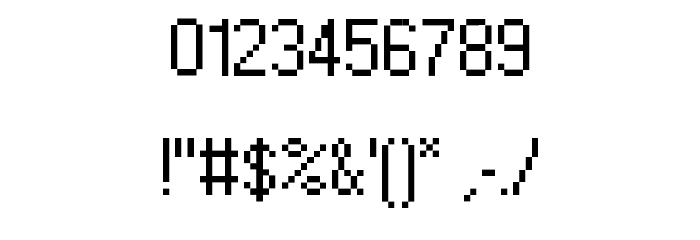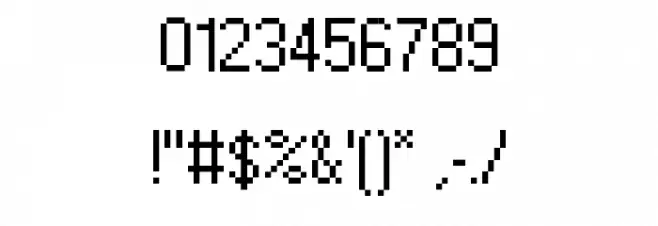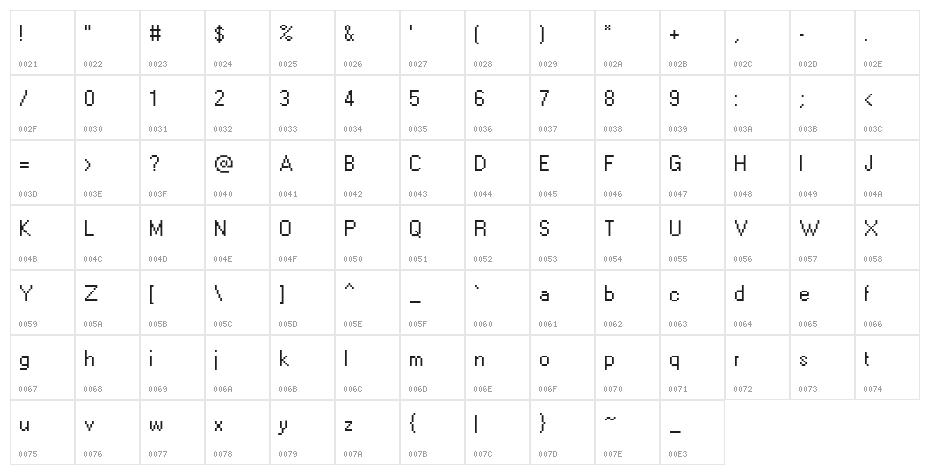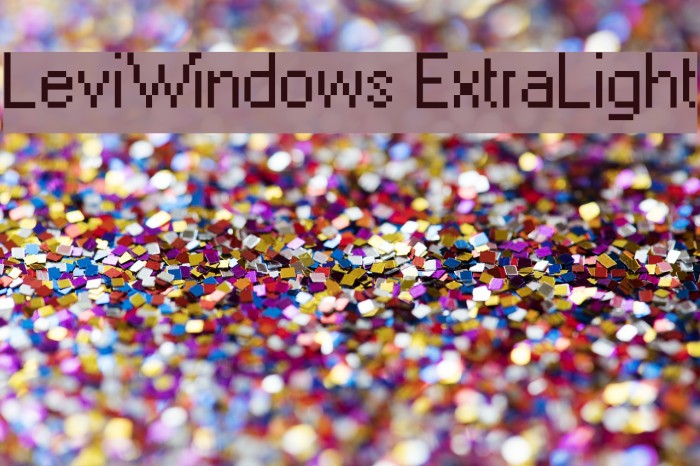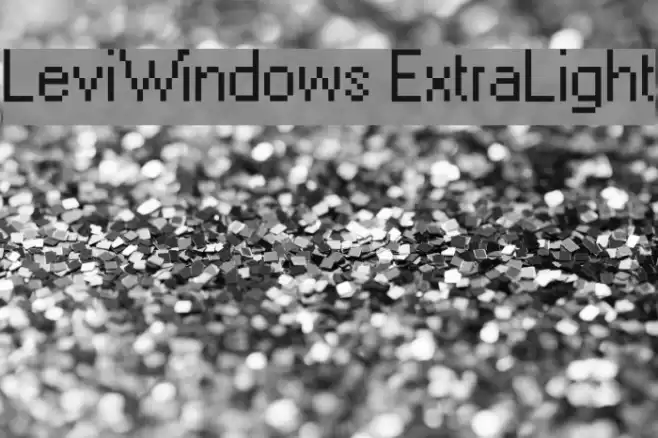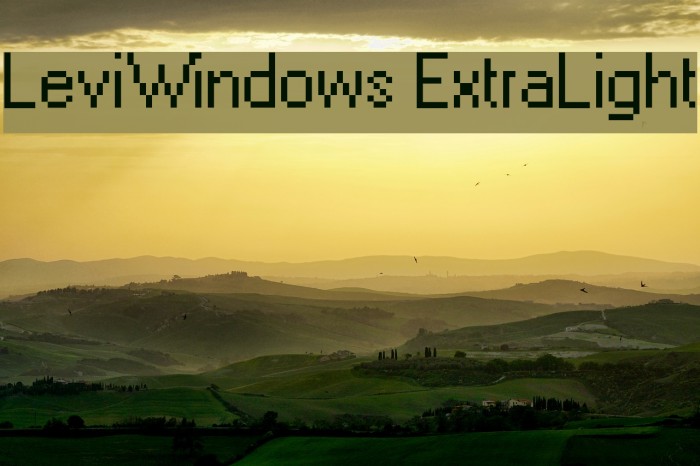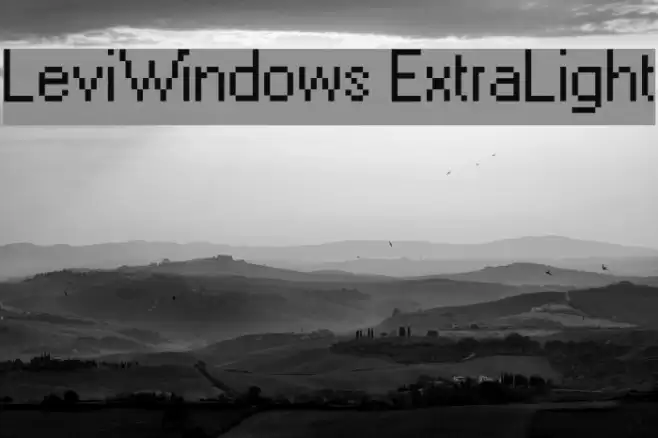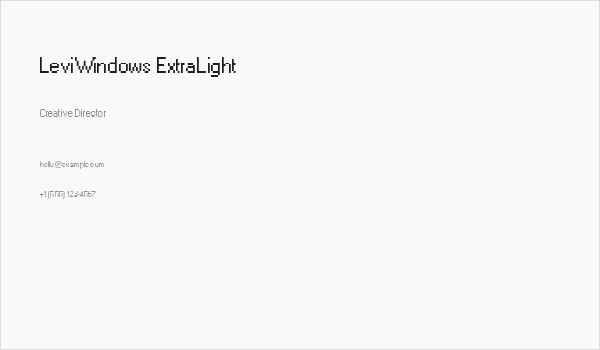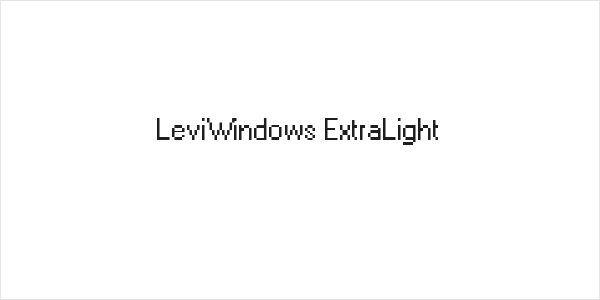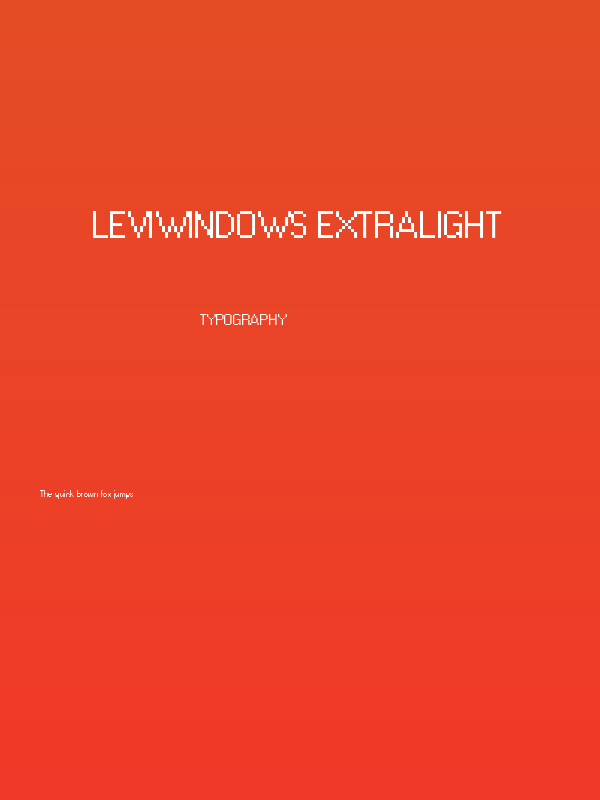
LeviWindows ExtraLight Font
| 分类 | Pixel |
| 整体风格 | Vintage |
| 使用场景 | Logos, Digital displays, Retro-themed designs |
| 推荐项目 | Ideal for retro video games, digital art projects, tech-themed posters, and any design requiring a vintage digital feel. |